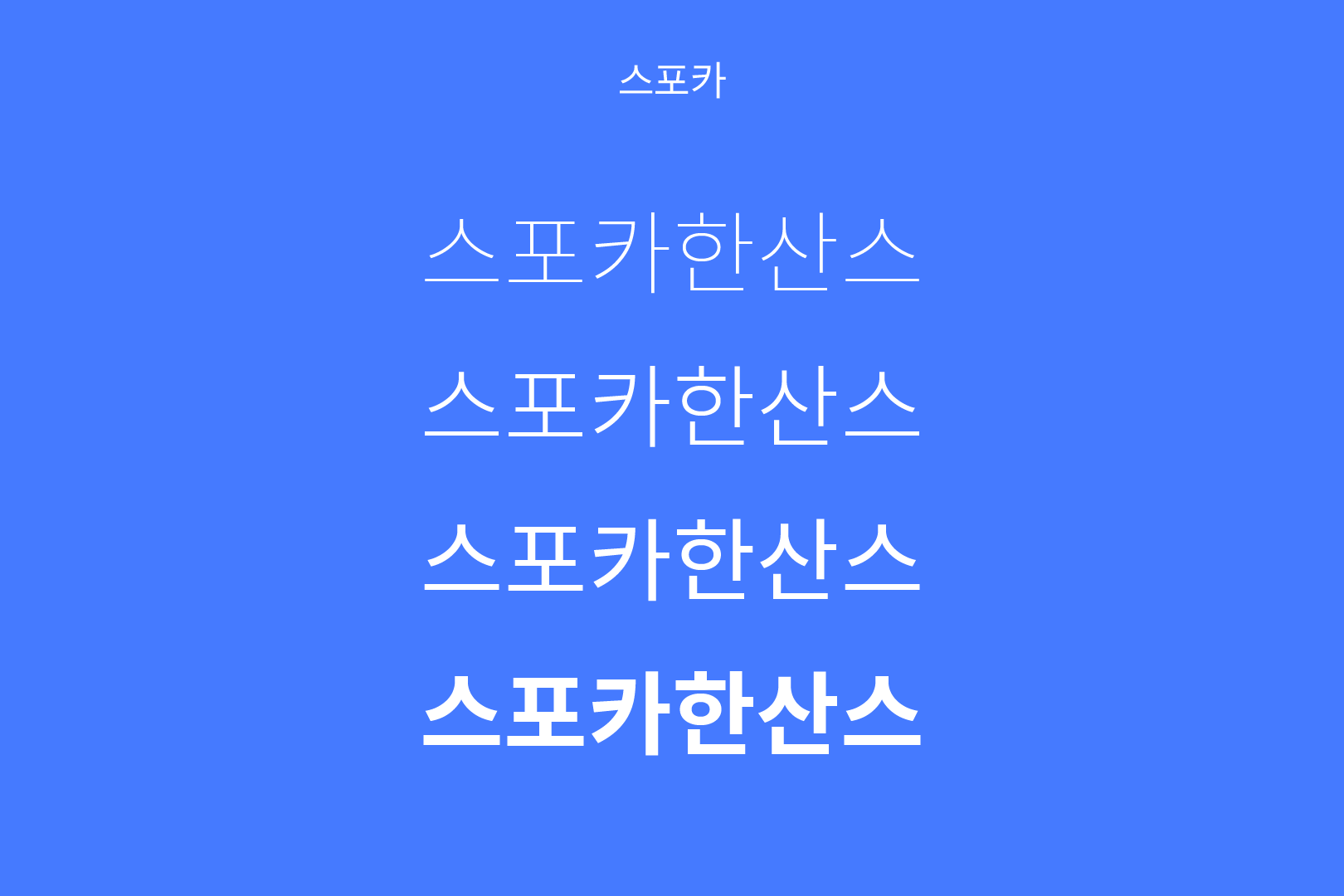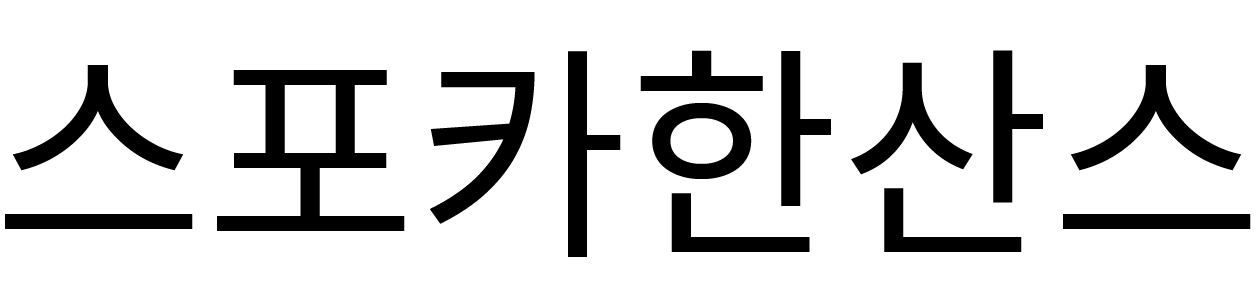
- 스포카 한 산스는 스포카 제품의 다국어 UI에 대응하기 위해 제작된 서체이다. 구글과 어도비의 합작 프로젝트로 제작된 본고딕(Source Han Sans)과 라토를 바탕으로 커스텀 디자인되었다.
폰트 정보 구분 고딕 글자구성 한글 2,350자
추가 글자 224자출시년도 2015